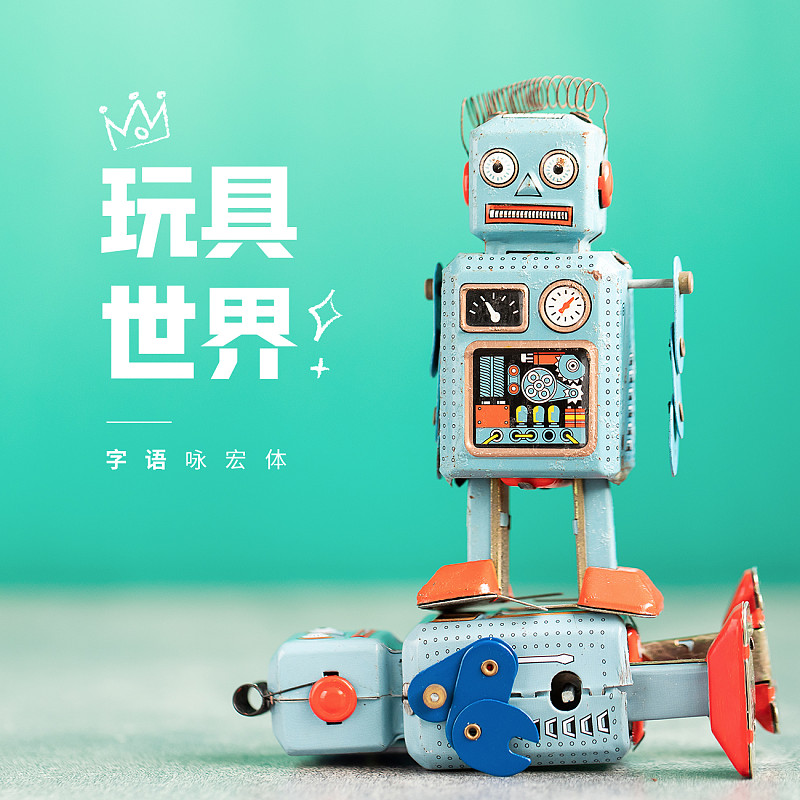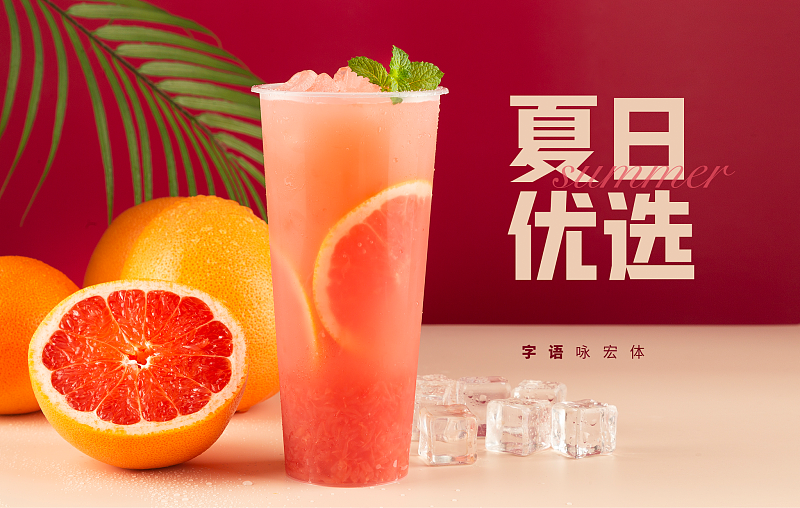
字語(yǔ)詠宏體
這款字的書(shū)寫(xiě)形態(tài),筆形棱角分明。適用于商場(chǎng)和網(wǎng)店的促銷(xiāo)廣告,以及兒童類(lèi)品牌的廣告和產(chǎn)品包裝的設(shè)計(jì)。
字體風(fēng)格:美術(shù)字體, 廣告字體
字體用途:廣告牌, 標(biāo)題